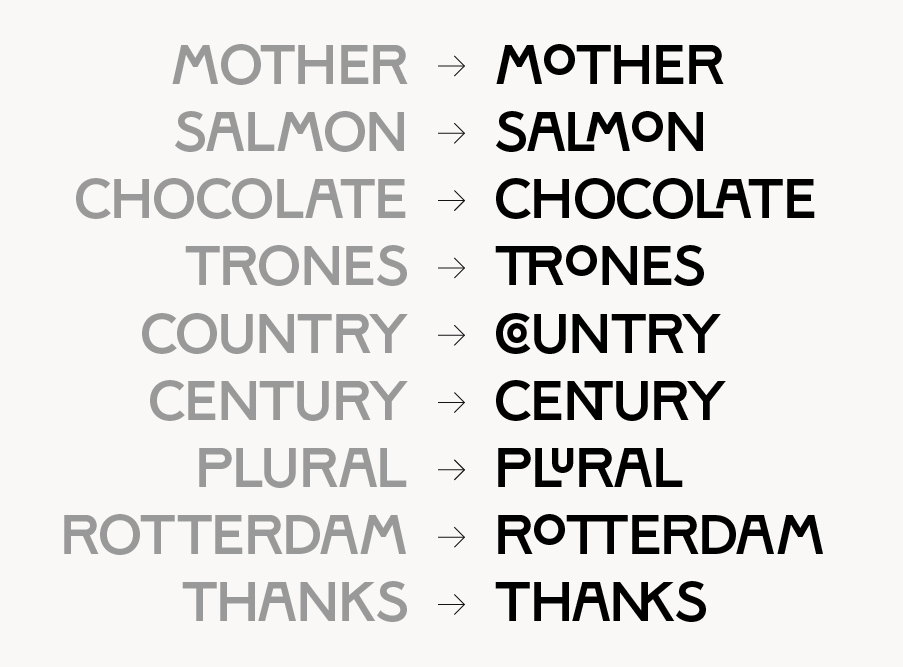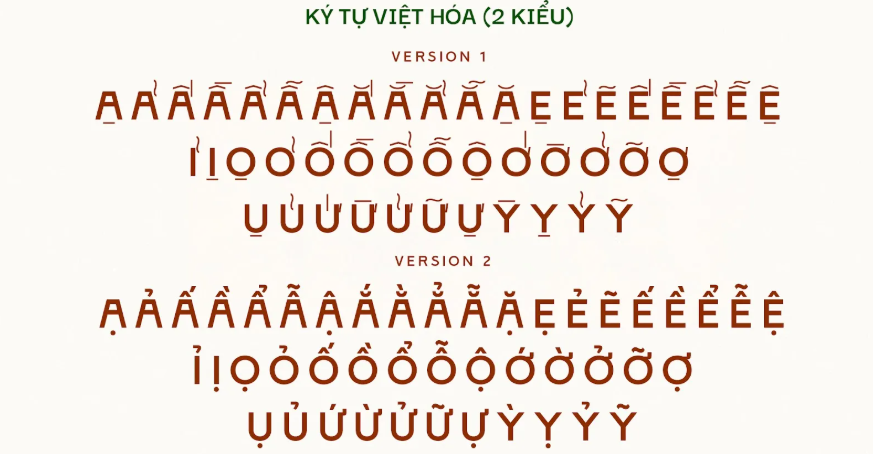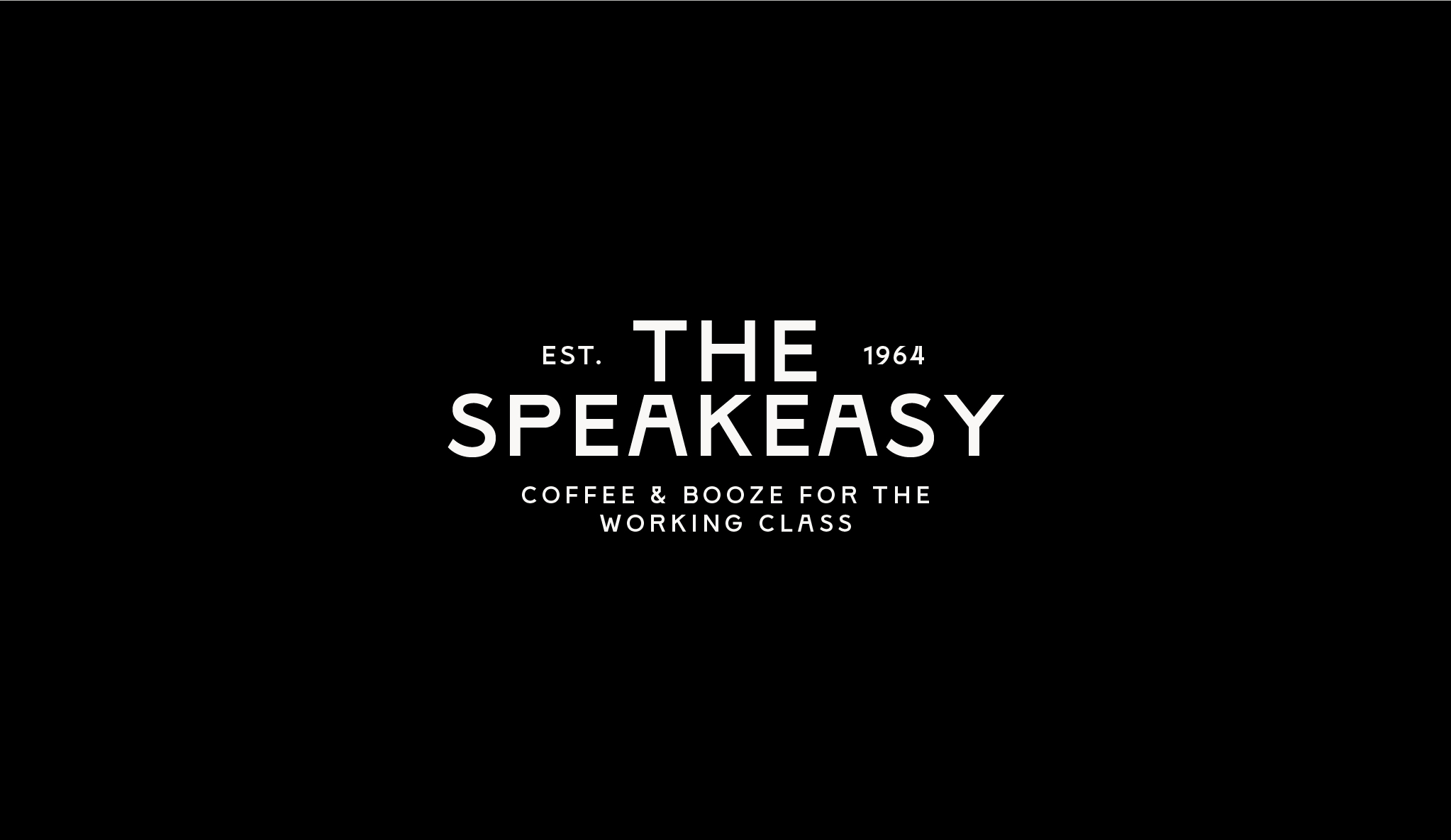
Đặc điểm thẩm mỹ độc đáo của bộ font Stampa
Stampa không đi theo sự bóng bẩy của các phông chữ hiện đại; nó tái hiện trọn vẹn vẻ đẹp thô mộc của các xưởng in truyền thống thế kỷ 20.
Phong cách con dấu công nghiệp thô mộc và mạnh mẽ
Đặc trưng lớn nhất của Font Stampa là cấu trúc chữ dày dặn kết hợp với các đường cắt stencil dứt khoát hoặc những gợn xước nhẹ mô phỏng bề mặt cao su dập mực. Hình khối chữ mang đậm tinh thần thực dụng, vững chãi và kỷ luật cao, tạo cảm giác như một con dấu niêm phong chất lượng trên các kiện hàng hàng hải xưa. Khi đặt Stampa làm tiêu đề trên bao bì, thương hiệu của bạn sẽ ngay lập tức toát lên vẻ nguyên bản, bền bỉ và tạo dựng niềm tin vững chắc về tay nghề thủ công.
Cấu trúc hình khối dứt khoát mang hơi thở cổ điển
Các ký tự của Stampa sở hữu tỷ lệ chữ cô đọng (Condensed), trục chữ hoàn toàn thẳng đứng cùng các góc cạnh vuông vức. Sự dứt khoát này mang lại sức nặng thị giác vượt trội, giúp các dòng thông số kỹ thuật, tên thương hiệu hay mã hiệu sản phẩm trên vỏ hộp hiển thị rõ ràng, uy lực và rất dễ nhận diện từ xa trên các kệ hàng trưng bày.
Ưu điểm nổi bật của bản font Stampa Việt hóa
Khi ứng dụng các phông chữ phong cách công nghiệp vào thị trường trong nước, sự chỉn chu về dấu câu là yếu tố quyết định đến tính chuyên nghiệp của bản thiết kế:
- Khắc phục triệt để lỗi dấu tiếng Việt: Phiên bản font Stampa Việt hóa đã được các chuyên gia trau chuốt thủ công từng dấu câu. Các dấu sắc, huyền, hỏi, ngã, nặng được thiết kế góc cạnh đồng điệu cùng thân chữ gốc, không gây cảm giác chắp vá hay làm mất đi tính hình khối chuẩn mực.